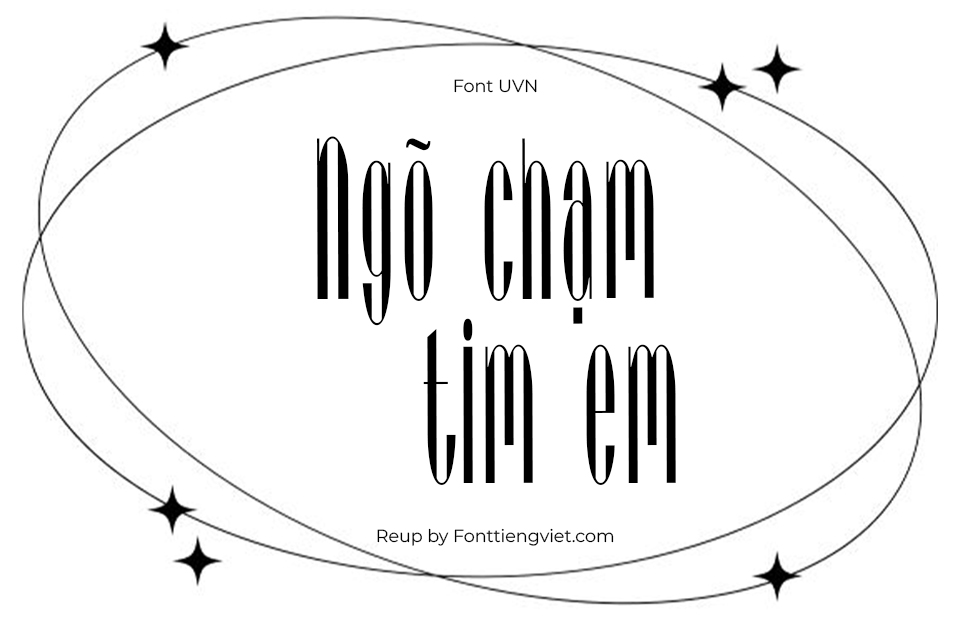
Font Việt Hóa UVN Thanh Binh – Sự Lựa Chọn Hoàn Hảo Cho Thiết Kế Giáo Dục
Giới thiệu về Font Việt Hóa UVN Thanh Binh
Trong thế giới thiết kế đồ họa tại Việt Nam, việc tìm kiếm một bộ Font Chữ vừa mang nét truyền thống vừa đảm bảo tính hiện đại là điều vô cùng quan trọng. Font Việt Hóa UVN Thanh Binh nổi lên như một giải pháp tối ưu cho những ai yêu thích sự thanh thoát và tinh tế. Đây là bộ phông chữ thuộc dự án UVN, được tinh chỉnh kỹ lưỡng để phù hợp hoàn toàn với bảng mã tiếng Việt, giúp người dùng không còn lo lắng về lỗi hiển thị dấu khi soạn thảo văn bản hay thiết kế ấn phẩm trường học.
Đặc điểm nổi bật của Font Việt Hóa UVN Thanh Binh
Phong cách thiết kế thanh lịch
Đúng như tên gọi “Thanh Bình”, bộ font này sở hữu những đường nét thanh mảnh, tạo cảm giác nhẹ nhàng và bình yên cho người xem. Cấu trúc chữ được xây dựng dựa trên tỷ lệ chuẩn, giúp văn bản trở nên dễ đọc và bắt mắt hơn trên cả nền tảng kỹ thuật số lẫn in ấn.
Ứng dụng đa dạng trong học tập và giảng dạy
Font Việt Hóa UVN Thanh Binh rất được ưa chuộng trong môi trường giáo dục. Giáo viên có thể sử dụng font này để thiết kế bài giảng điện tử, làm bằng khen hoặc trang trí bảng tin lớp học. Các em học sinh cũng thường xuyên lựa chọn phông chữ này để trình bày báo tường hoặc làm tiêu đề cho các bài tiểu luận sáng tạo nhờ tính thẩm mỹ cao và sự trang trọng mà nó mang lại.
Kết luận về bộ font chữ quốc dân